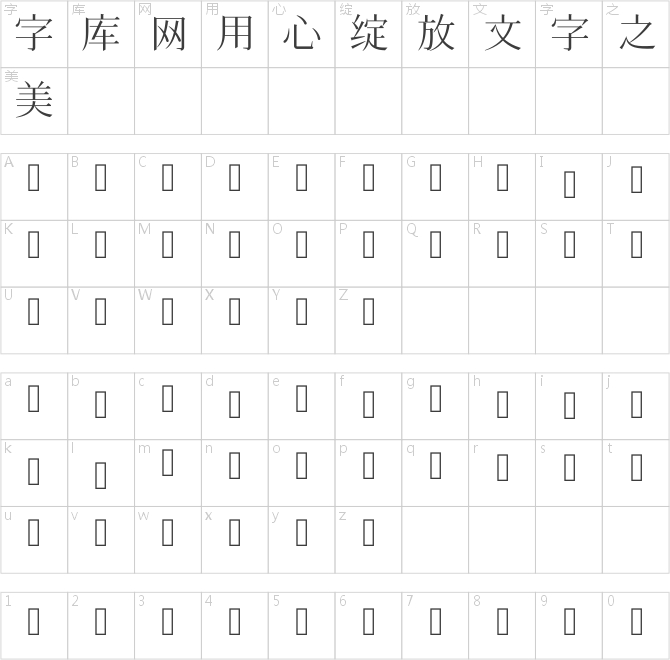
醍醐书体
醍醐书体介绍
是由字形维基网友们共同发起制作的“醍醐书体”,该字型以“宋体”的样式为主,而且收录的字符数量也是超级多的,也是一款超大字符集的字体。
而字形维基(GlyphWiki)是一个自由的所有人都可以共享的维基,旨在对宋体(明朝体)的汉字字形进行登记与管理。
汉字字形的管理一般很麻烦,但在字形维基,您可以简单地编辑汉字,可以逐个管理汉字字形,一切尽在同一个维基。
所有人都可以进行汉字的管理。而且,已有的字形所有人都可以自由使用。可以制作上传自己需要的字形,和已有的数据合在一起,结合起来将制成一个字体。字形维基现有超过58万个字形,别名同字形分别计数。同字合并后则是34万余字。
字体包中有两个字体文件,分别是醍醐书体A.ttf、醍醐书体B.ttf,这两个字体几乎囊括了整个unicode字符集。 醍醐书体B包含扩展B区字符。